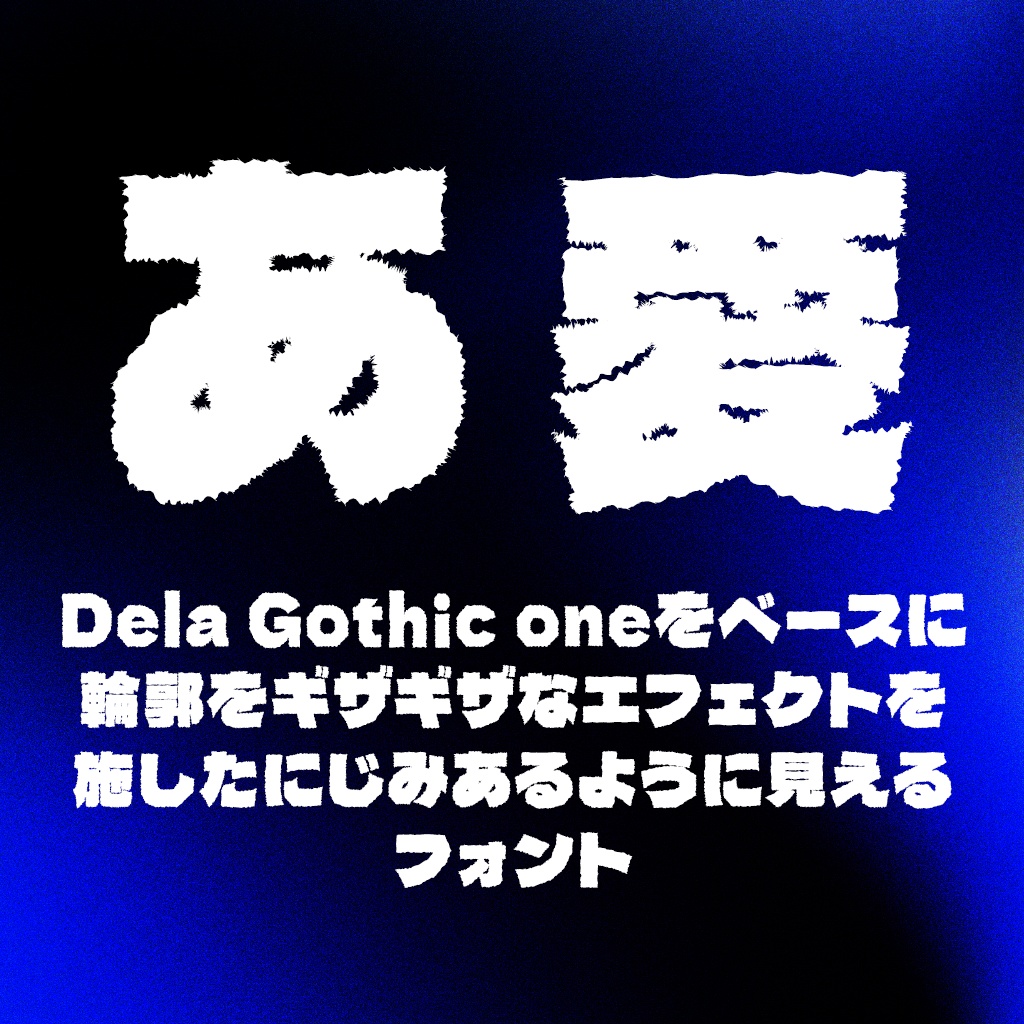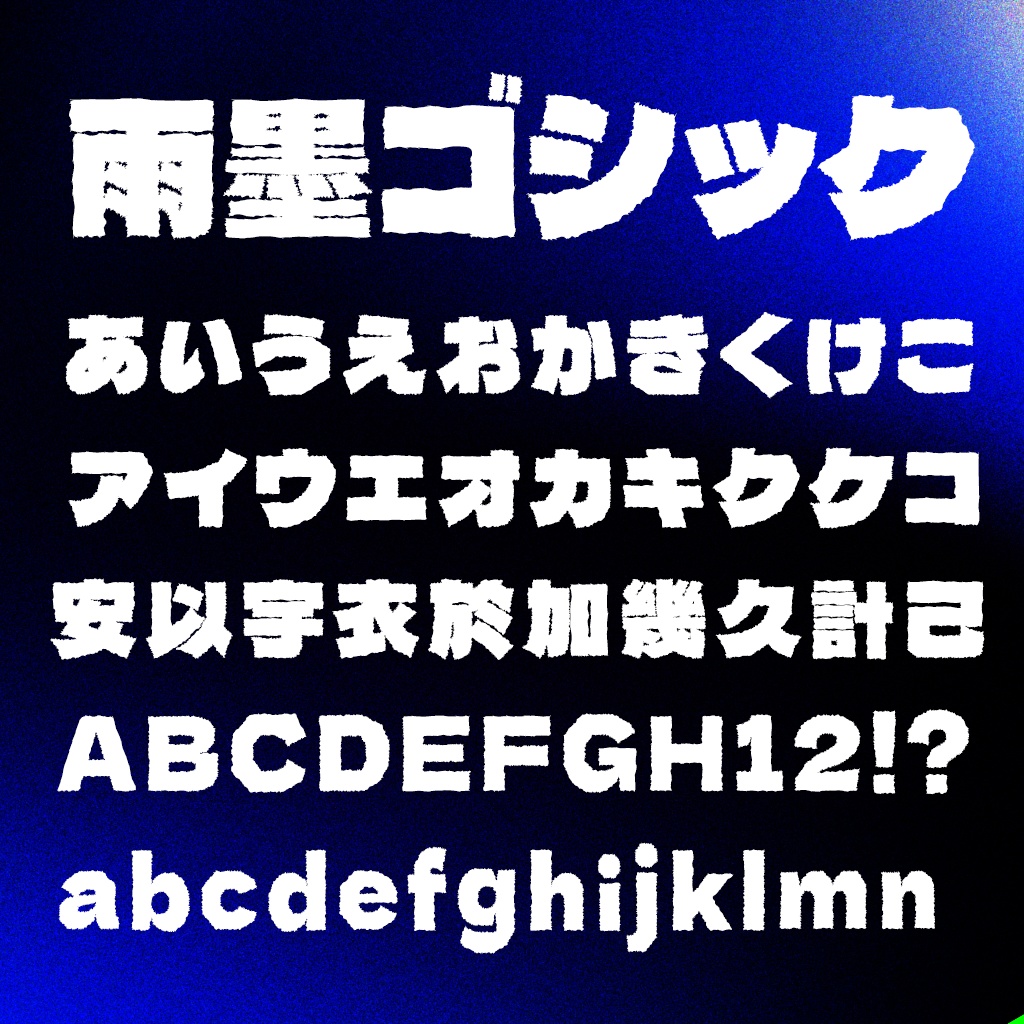
雨墨ゴシック(フリーフォント)
【25.04.17更新】 ・一部の文字が欠陥していましたので修正対応いたしました。 --- 【概要】 雨墨ゴシックは、デラゴシック(Dela Gothic One)を改変したフリーフォントです。 文字の輪郭を手書きっぽさのある手書きな雰囲気にしつつ、凸凹に変形させたフォントです。輪郭が墨のように滲んでいるようにも見えるフォントです。 無料版と投げ銭版(¥500)のフォント内容は同一です。 【ライセンス・規約について】 このフォントはSIL Open Font License 1.1で公開されています。 個人・商用にかかわらず無償で使用可能で、動画・サムネイル・ゲーム等への組み込みなどご自由にご利用ください。 詳しいSILライセンスについてはサイトをご確認ください。 https://licenses.opensource.jp/OFL-1.1/OFL-1.1.html 当フォントを利用して発生した、いかなる損害についても作者は責任を負いません。 フォントデータをダウンロードした時点で利用規約に同意したものとみなします。 【改変元フォント】 デラゴシック(Dela Gothic One) 関係者に深くお礼申し上げます。